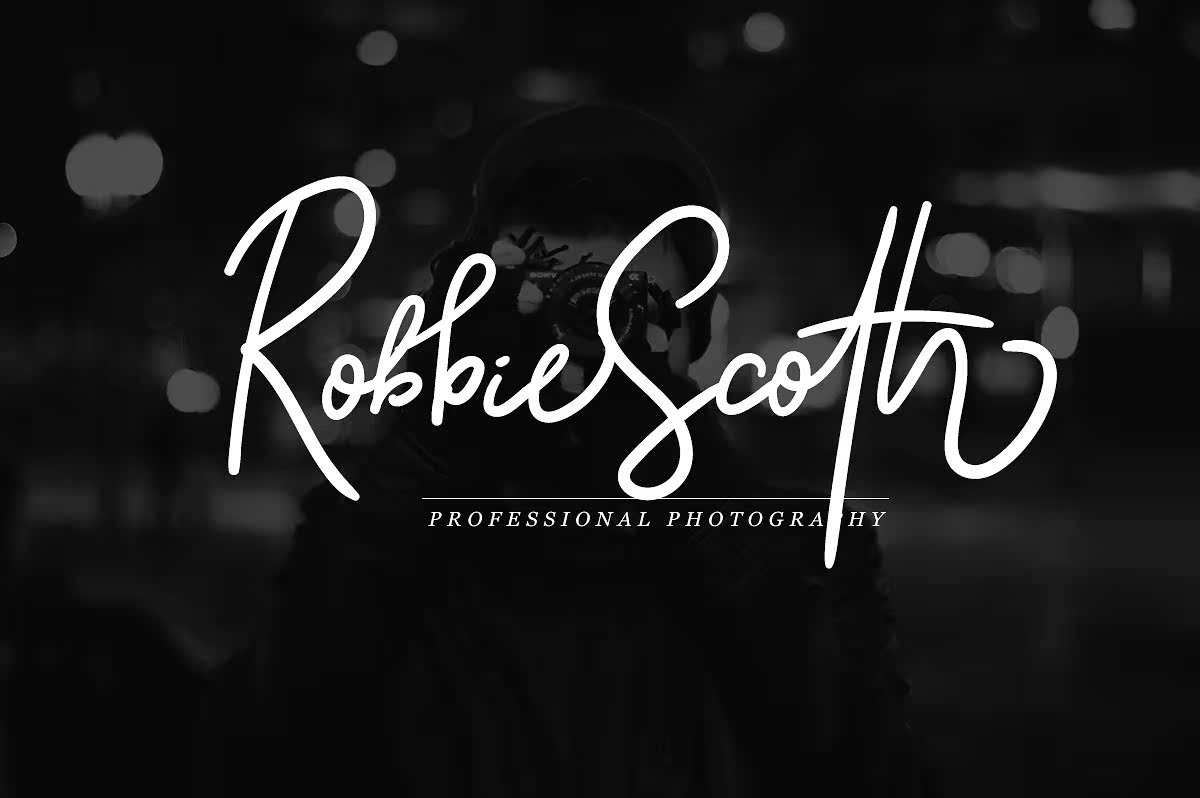
Gloriant签名脚本字体,有两种字体:干净和刷子!外观和文雅都是自然的设计和书写。此字体适用于任何设计目的,如徽标、标题、引语、服装、婚礼宣传,当然还有您的数字签名。华丽的签名文字字体具有五种特征:模仿、风格替代、背景替代、虚饰、,ETC支持多语言。有关详细信息,请查看第三次预览。Gloriant签名脚本字体有两种字体:clean和brush!外观和文雅都是自然的设计和书写。此字体适用于任何设计目的,如徽标、标题、引语、服装、婚礼宣传,当然还有您的数字签名。华丽的签名文字字体具有五种特征:模仿、风格替代、背景替代、虚饰、,ETC支持多语言。有关详细信息,请查看第三次预览。